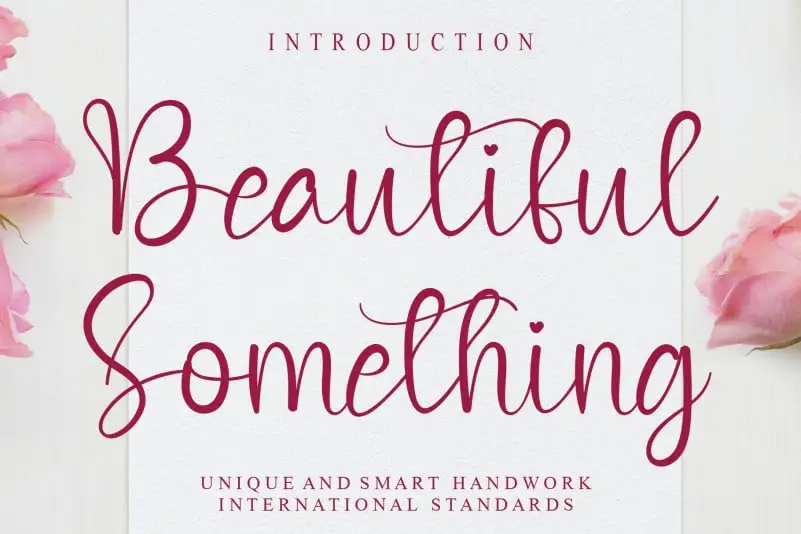
Beautiful Something Calligraphy Font – Download Grátis
Aqui está uma descrição para a página de download da fonte ‘Beautiful Something Calligraphy Font’ na categoria Script Fonts: A fonte Beautiful Something Calligraphy é uma escolha perfeita para aqueles que valorizam a arte e sofisticação nas suas criações digitais. Inspirada em uma mistura única de elegância e criatividade, esta fonte oferece linhas finas e leves que se transformam em textos suaves e delicados. Com um design cuidadosamente elaborado, Beautiful Something Calligraphy traz à vida qualquer texto com uma expressividade ímpar. Suavemente arredondada e harmoniosamente perfeita, esta fonte permite criar texturas suaves sem perder a precisão que tanto os designers como os amantes da arte valorizam. Para quem busca um toque especial em seus projetos digitais, Beautiful Something Calligraphy é uma excelente opção para adicionar profundidade e personalidade. Seja para gráficos de mídia social, design editorial ou até mesmo ilustrações, esta fonte traz um ar elegante que certamente fará seu trabalho. Beautiful Something Calligraphy é a escolha perfeita para quem busca algo novo em sua biblioteca de fontes, seja para celebrar o momento especial da sua criação ou simplesmente adicionar um toque único e sofisticado.